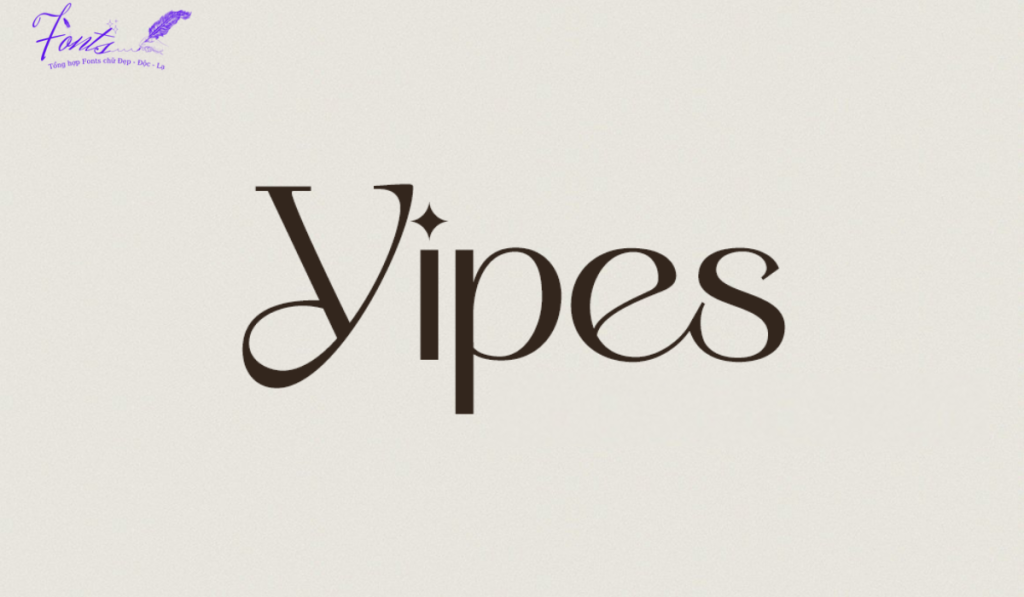
Font SVN Yipes
Tác giả: Three Islands Press
Ngày phát hành: 2022
Phân loại: Hiện đại, Thanh lịch
Kiểu chữ: Serif
Độ dày: Regular, Bold, Italic
Font SVN Yipes thuộc bộ font SVN, là kiểu chữ có chân mang phong cách tinh tế và sang trọng.